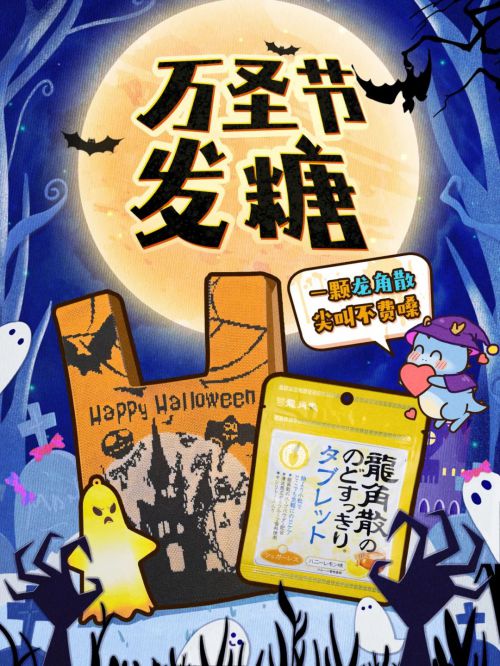
点字小轻松
点字小轻松是由点字库推出的创意字体,以卡通可爱的风格与有趣的设计巧思,成为年轻化场景的理想选择。字形修长挺拔,重心居中稳定,中宫设计适中,既保留了字体的舒展感,又避免了松散;笔形融合直角切割与斜切设计,搭配灵动的装饰元素,方头笔画与尖锋收笔形成鲜明对比,笔画间的断开处理更添俏皮韵律。细线条为主的笔画中暗藏粗细变化,让字体在轻盈中透出层次感,整体视觉轻松舒适,兼具活泼张力。 作为会员商用授权字体,点字小轻松适用于欢快主题标题、娱乐活动宣传、儿童读物排版等场景,其卡通化的笔形语言与趣味性设计,能快速传递轻松愉悦的氛围,为设计注入鲜活活力,是打造年轻化视觉符号的优质选择。
卢鑫亚
90后字体设计师,曾获第二届字体之星评委奖,最具商业潜力奖,第三届字体之星评委奖。